Font manga việt hoá là bộ sưu tập các phông chữ chuyên dụng được thiết kế và địa phương hóa để phục vụ cho việc dịch thuật truyện tranh (scanlation), thiết kế webtoon, poster anime và bao bì sản phẩm mang phong cách Nhật Bản. Từ các dòng phông chữ hội thoại rõ nét trong bong bóng chat cho đến các kiểu chữ hiệu ứng âm thanh (SFX) bùng nổ, nhóm phông chữ này là công cụ không thể thiếu cho các nhóm dịch thuật và các nhà sáng tạo merchandise. Doozypack.vn cung cấp link tải trọn bộ font manga việt hoá chuẩn kỹ thuật, giúp bạn sở hữu các phông chữ độc đáo, hỗ trợ đầy đủ tiếng Việt không lỗi dấu để hiện thực hóa mọi ý tưởng thiết kế ấn tượng.
Phân loại các nhóm font manga việt hoá phổ biến nhất
Trong thế giới truyện tranh, Typography đóng vai trò dẫn dắt cảm xúc người đọc. Việc phân loại chính xác giúp bạn chọn đúng phông chữ cho từng ngữ cảnh biểu đạt.
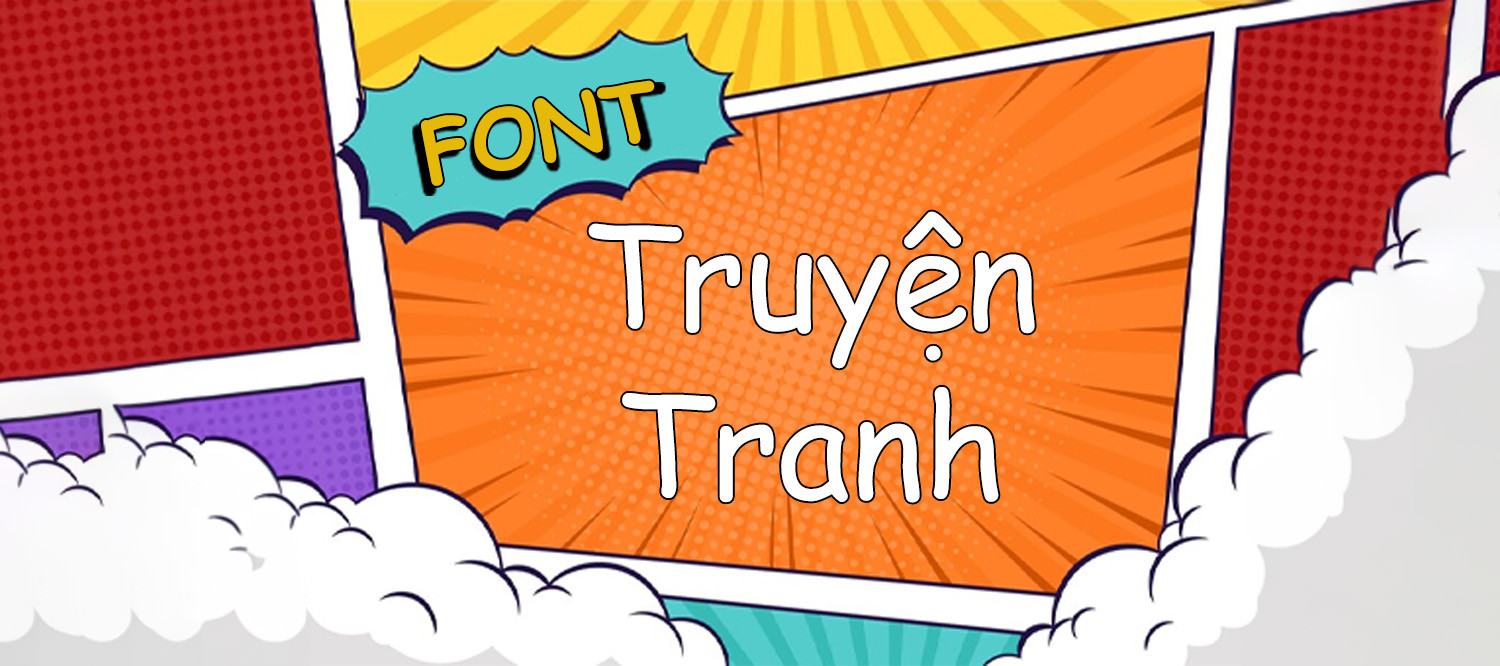
Font thoại truyện tranh (Dialogue fonts) rõ nét trong bong bóng chat
Đây là nhóm phông chữ không chân (Sans-serif) hoặc Serif tối giản, được thiết kế với cấu trúc x-height lớn, các khoảng hở rộng giúp người đọc dễ dàng theo dõi các đoạn hội thoại dài mà không bị mỏi mắt. Các dòng phông chữ này thường mang tính trung tính, đôi khi hơi ngẫu hứng để phù hợp với tâm trạng của nhân vật nhưng vẫn bảo đảm tính minh bạch tuyệt đối trong các ô thoại.
Font sfx manga Việt hóa & Font Manga 6 bùng nổ
Đối với các cảnh hành động, cao trào hoặc biểu cảm mạnh, Font sfx manga Việt hóa và Font Manga 6 Việt hóa là “vũ khí” tối thượng. Nhóm phông chữ này sở hữu độ dày nét cực lớn, các đường cắt vát sắc sảo hoặc hiệu ứng khối 3D, mô phỏng lại tiếng động (như Bùm, Choang, Rầm) vô cùng sống động, giúp tăng gấp đôi sức nặng thị giác cho trang truyện hoặc các thiết kế bao bì merchandise anime.
Ưu điểm nổi bật của bộ font manga việt hoá
Khi ứng dụng các phông chữ truyện tranh quốc tế vào thị trường trong nước, sự chỉn chu về dấu câu là yếu tố quyết định đến tính chuyên nghiệp của ấn phẩm:
- Khắc phục triệt để lỗi dấu tiếng Việt: Phiên bản Việt hóa đã được đội ngũ thiết kế trau chuốt thủ công từng dấu câu. Các dấu sắc, huyền, hỏi, ngã, nặng được vẽ bám sát với thân chữ, không gây cảm giác chắp vá hay làm đè nét lên các ký tự bên cạnh.
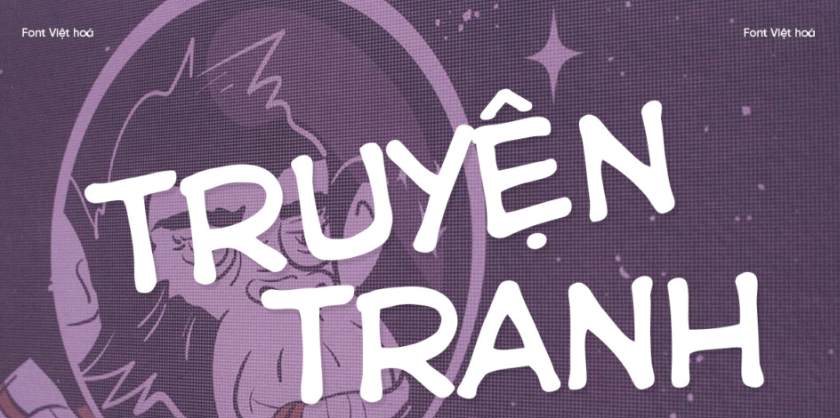
| Nhóm Font Manga | Đặc điểm thị giác | Ứng dụng đề xuất tại Doozypack.vn |
| Font Thoại (Dialogue) | Sạch sẽ, minh bạch, dễ đọc | Dùng cho lời thoại trong bong bóng chat, văn bản mô tả. |
| Font SFX Hành động | Góc cạnh, bùng nổ, uy lực | Làm tiêu đề chính hộp quà anime, poster sự kiện. |
| Font Manga 6 Series | Đậm đà, cá tính, độc bản | Thiết kế bao bì merchandise, sticker, standee nhân vật. |
Ứng dụng thực tế của font manga trong sản xuất bao bì tại Doozypack.vn
Sự độc đáo và giàu cảm xúc của các bộ font manga mang lại hiệu ứng thị giác đắt giá trên các dòng sản phẩm bao bì thực tế do Doozypack.vn sản xuất:
- Hộp giấy đựng Mô hình nhân vật (Figures) & Artbook: Tiêu đề thương hiệu in bằng font SFX kết hợp kỹ thuật in phủ UV định hình trên giấy Ivory đen tạo nên vẻ ngoài vô cùng cao cấp và đậm chất anime.
- Bao bì Thẻ bài (Trading Cards) & Phụ kiện game: Tên dòng sản phẩm in bằng font manga tạo cảm giác hiện đại, đậm chất thể thao điện tử và khơi gợi niềm đam mê của cộng đồng otaku.
- Túi giấy sự kiện & Quà tặng Cosplay: Dùng cho tên cửa hàng in trên nền túi giấy tối màu mang lại phong cách huyền bí, tinh tế và khẳng định gu thẩm mỹ độc đáo.
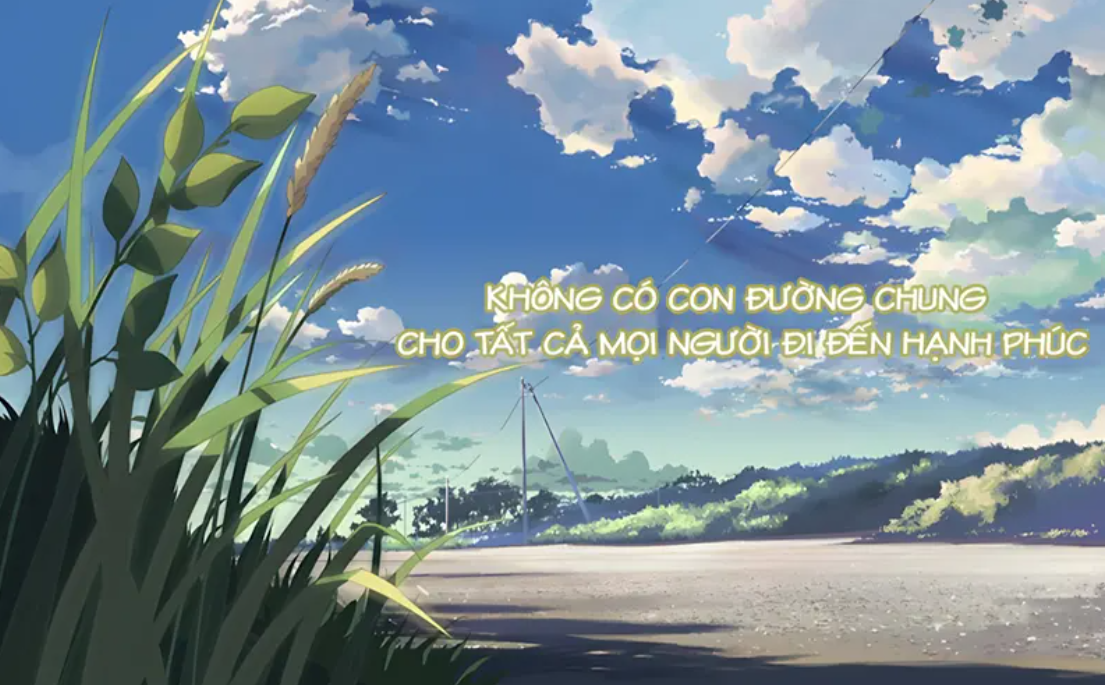
03 Lưu ý kỹ thuật khi in ấn với phông chữ truyện tranh và SFX
Việc sản xuất bao bì thực tế sử dụng các phông chữ mang tính biểu diễn cao đòi hỏi sự am hiểu kỹ thuật chuyên sâu tại xưởng in Doozypack.vn:
- Kiểm soát độ phân giải khi in ấn: Đối với các hiệu ứng âm thanh (SFX) có kích thước lớn, hãy luôn đảm bảo hình ảnh và chữ viết đạt độ phân giải tối thiểu 300 DPI để tránh hiện tượng vỡ hạt khi in Offset.
- Lựa chọn chất liệu giấy phẳng mịn: Các phông chữ manga đẹp nhất khi in trên giấy Ivory, Couche hoặc giấy mỹ thuật nhẵn. Bề mặt giấy phẳng mịn sẽ giúp từng đường nét góc cạnh hiển thị sắc lẹm, không bị nhòe mực.